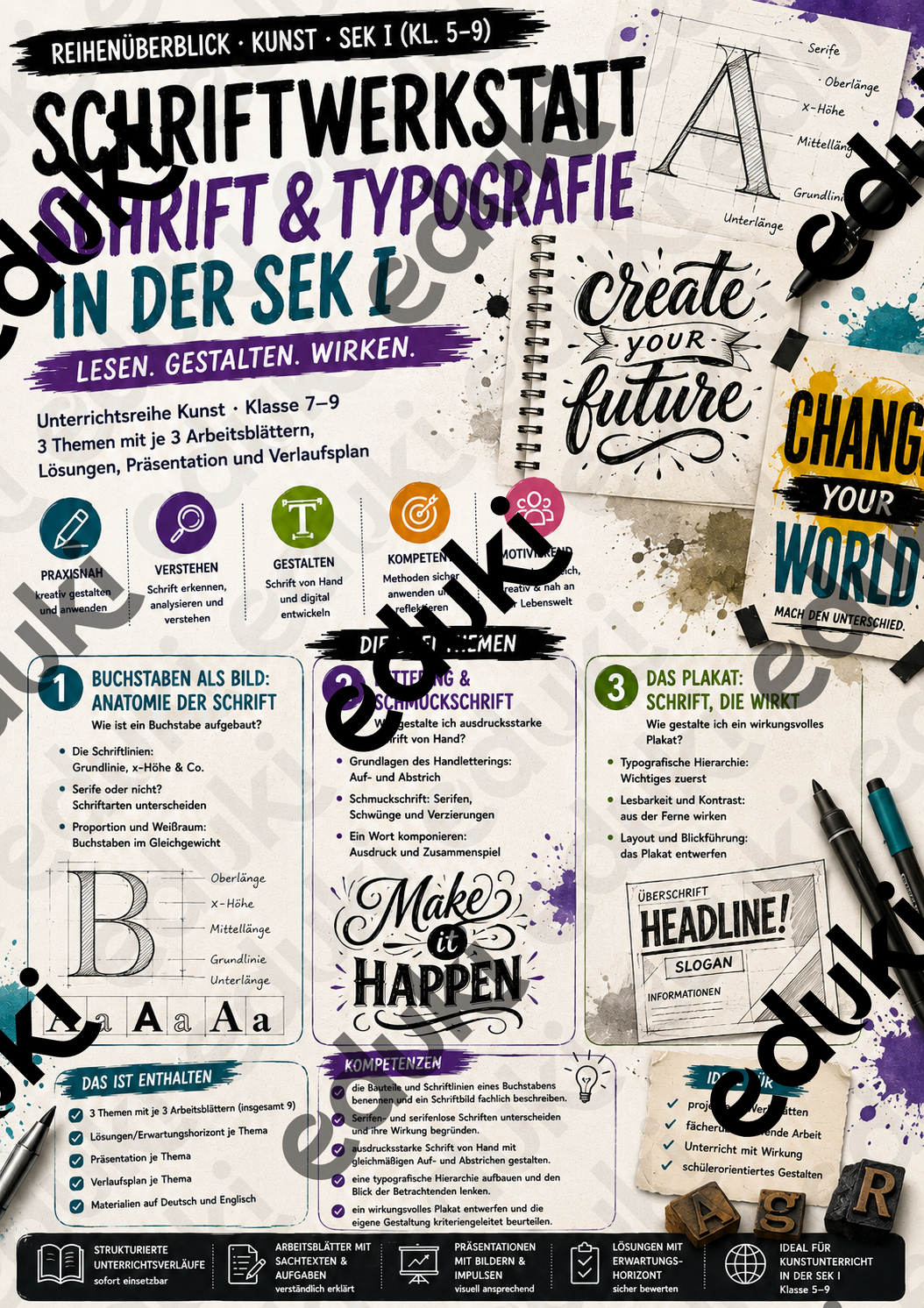
Schrift ist weit mehr als Information. Sie transportiert Emotionen, lenkt Aufmerksamkeit und prägt die Wirkung von Plakaten, Logos, Werbeanzeigen und digitalen Medien. Diese Unterrichtsreihe führt Schülerinnen und Schüler praxisnah in die Welt der Typografie und Schriftgestaltung ein und zeigt, wie Gestaltung und Kommunikation miteinander verbunden sind.
Zu Beginn lernen die Schülerinnen und Schüler den Aufbau von Buchstaben kennen. Sie beschäftigen sich mit Schriftlinien, Proportionen, Weißraum sowie serifenlosen und Serifenschriften und erkennen, wie unterschiedliche Schriftarten verschiedene Wirkungen erzeugen. Anschließend entwickeln sie eigene Letterings und experimentieren mit Strichstärken, Verzierungen und dekorativen Schriftformen. Im dritten Themenbereich gestalten sie ein professionell wirkendes Plakat und lernen, wie typografische Hierarchien, Kontraste und Layouts den Blick der Betrachterinnen und Betrachter gezielt lenken.
Neben den praktischen Gestaltungsaufgaben erwerben die Lernenden wichtige Kompetenzen der visuellen Kommunikation. Sie analysieren Schriftwirkungen, entwickeln eigene Designideen und setzen Typografie gezielt als Gestaltungsmittel ein. Gleichzeitig werden Kreativität, Gestaltungsbewusstsein, Medienkompetenz und grafisches Denken gefördert.
Die Unterrichtsreihe eignet sich ideal für einen modernen Kunstunterricht und verbindet klassische Schriftgestaltung mit aktuellen Designprinzipien aus Werbung, Grafikdesign und digitalen Medien.
Anatomie der Schrift
Schriftlinien
Serifen und serifenlose Schriften
Proportion und Weißraum
Handlettering
Schmuckschrift
Typografie
Typografische Hierarchie
Plakatgestaltung
Layout und Blickführung